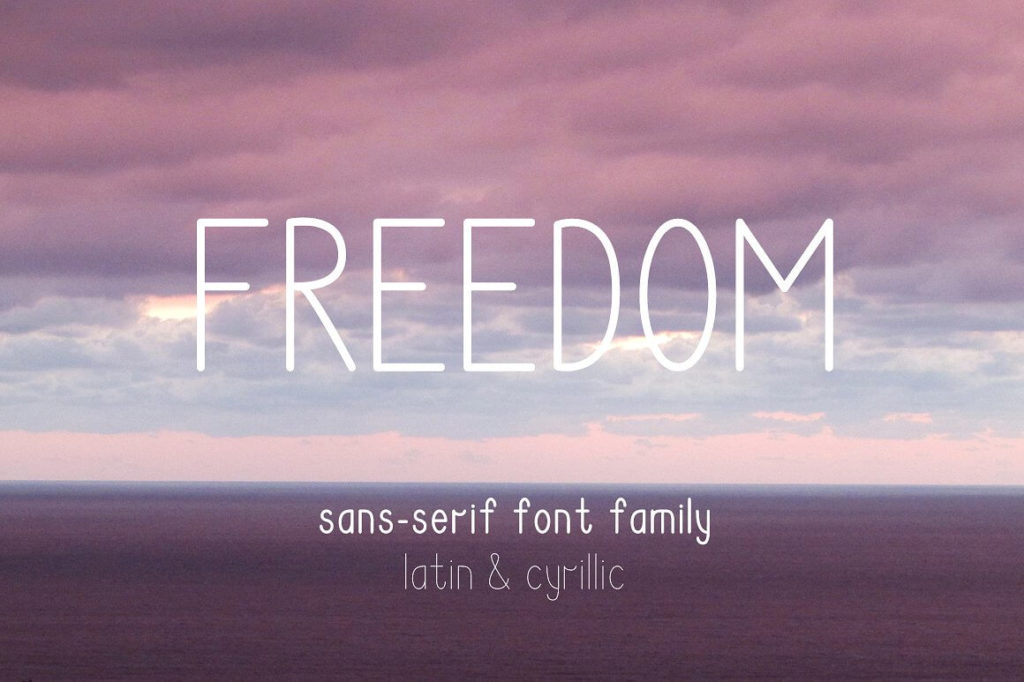
Это выразительный рукописный шрифт от студии Fanastudio, адаптированный для набора текстов на кириллице. В основе начертания лежат плавные, динамичные линии, имитирующие естественное письмо кистью или пером. Этот шрифт сочетает в себе неформальность рукописного стиля с высокой читаемостью и элегантностью, что делает его отличным выбором для создания уникального визуального образа. Он идеально подходит для заголовков, логотипов и акцентных текстов, где важно передать тепло, индивидуальность и современный стиль. Вы можете скачать бесплатно кириллическую версию шрифта Freedom на нашем сайте и начать использовать его в своих проектах уже сегодня